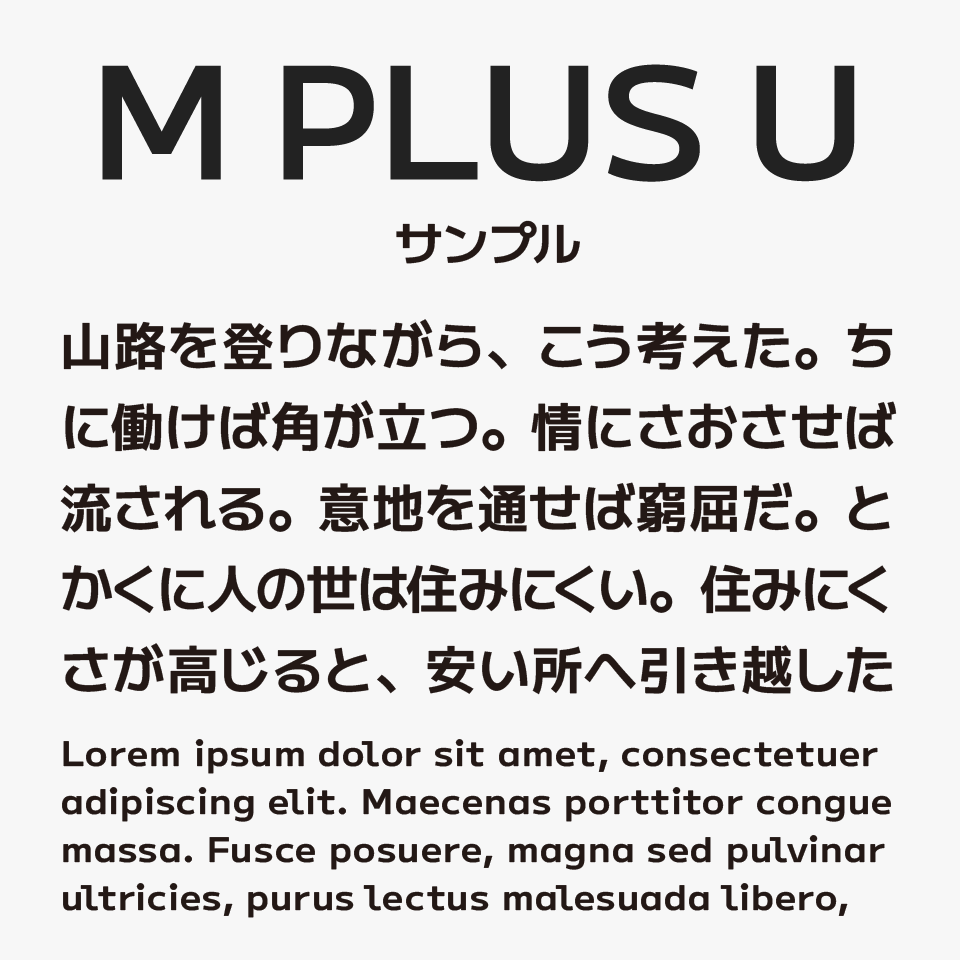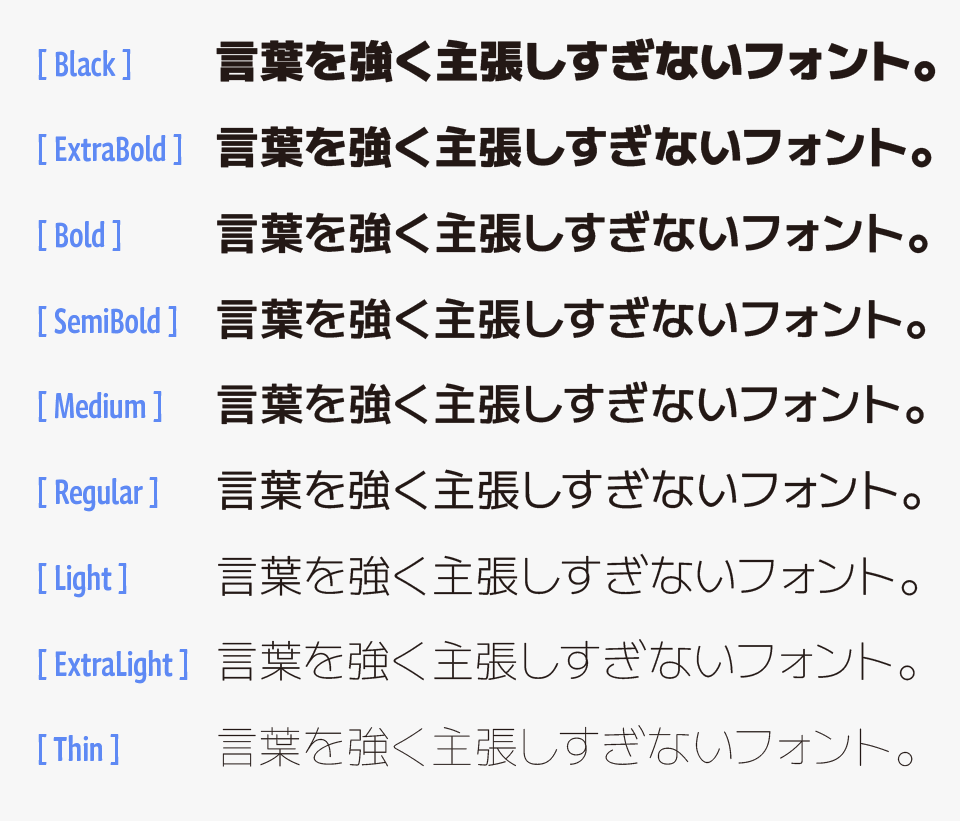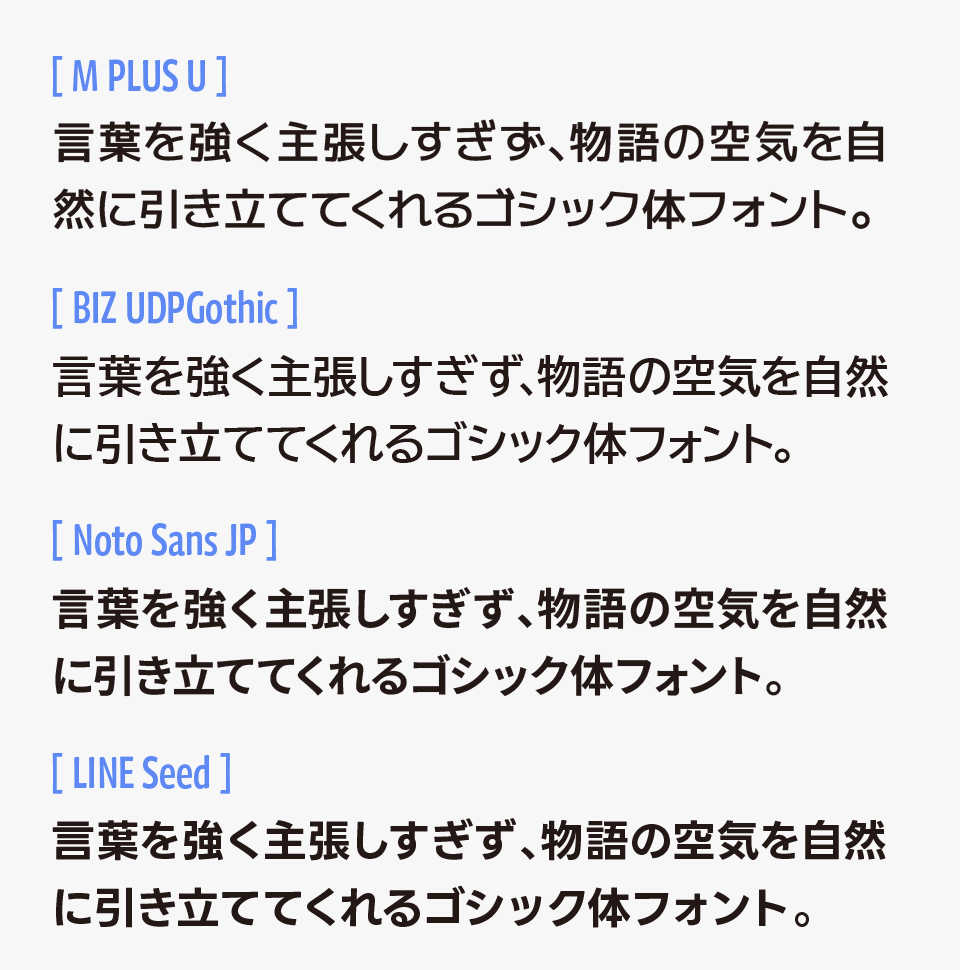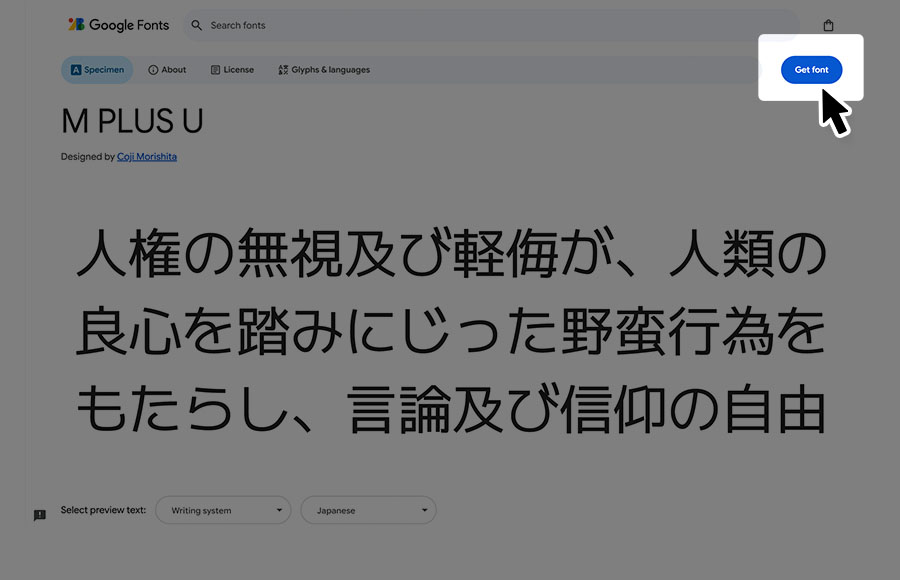
M PLUS Uフォントは、すっきりとした読みやすさと、ほんのり可愛らしさを兼ね備えた、ユニバーサルデザインを意識して制作されたUDフォントです。
ユニバーサルデザイン向けに制作されたフォントなので、視認性の高さを重視して設計されており、一文字一文字の形が非常に整っているため、小さなサイズでも読みやすく、長文でもストレスなく読むことができます。
シンプルでクセのないデザインながら、どこかやわらかな印象があり、堅すぎず親しみやすい雰囲気を感じられるフォントです。
多くの人にとって見やすく認識しやすい設計になっているため、Webデザインや資料制作、アプリUI、教育関連、案内表示など幅広い場面で活躍します。実用性の高さとやさしいデザイン性を両立した、とても使いやすいフォントとなっています。
M PLUS U
ウェイトが、ThinからBlackはで9種類用意されており、さらにバリアブルフォントにも対応しています。
M PLUS Uのウェイトが9種類
M PLUS Uフォントを、ほかのユニバーサルデザインフォントや一般的なゴシック体フォントと比較してみると、はっきりと整理された字形の中にもほどよいやわらかさがあり、実用性だけでなくデザイン性も感じられるところが特徴のフォントです。
比較フォントは、「BIZ UD GOTHIC」「Noto Sans JP」「LINE Seed」と使用していますが、どれも特徴的な明朝体フォントなので、ぜひあわせてチェックしてみてください。
M PLUS Uと「BIZ UD GOTHIC」「Noto Sans JP」「LINE Seed」フォントを比較